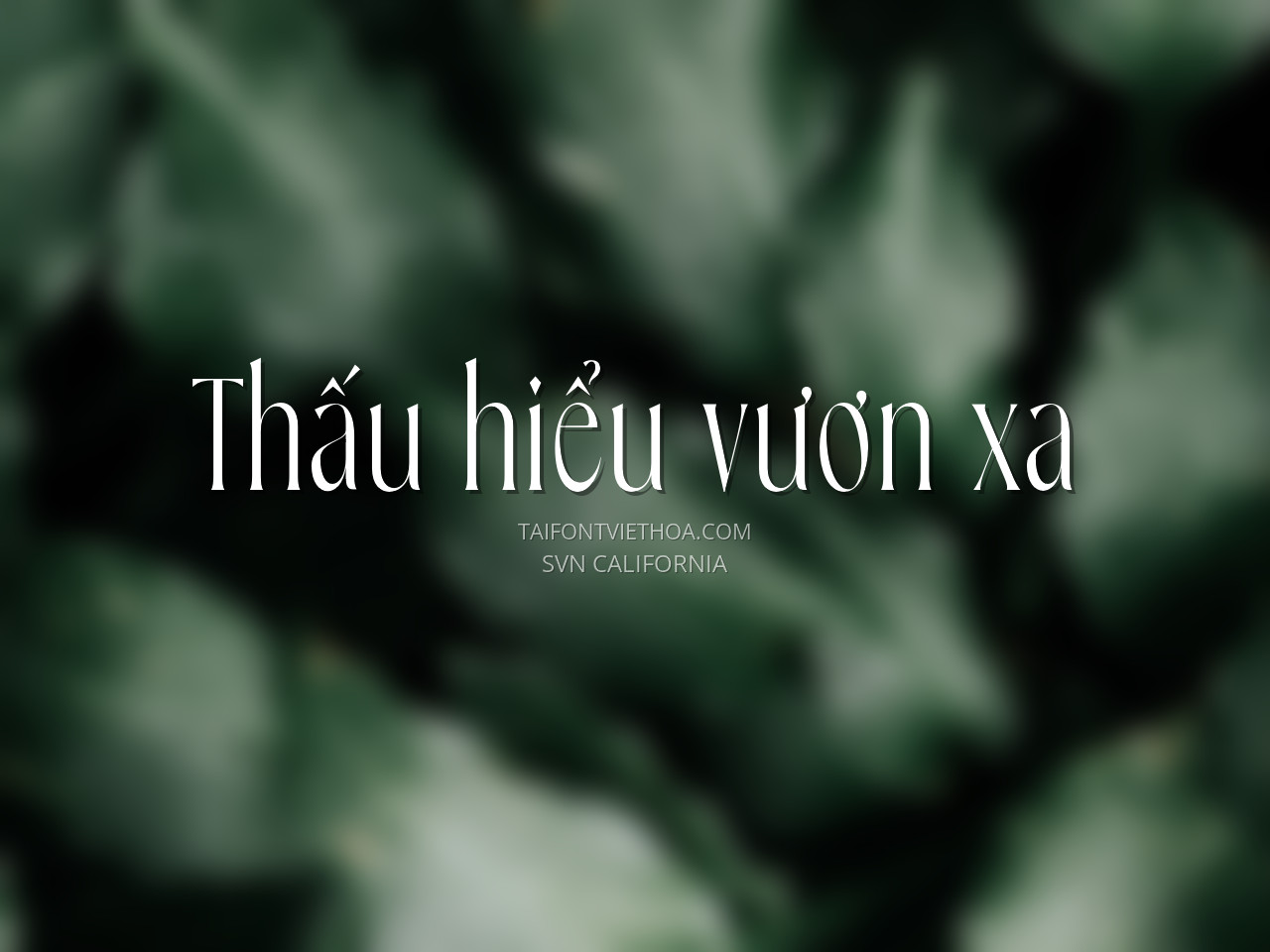
Font việt hóa SVN California
Giới thiệu về font SVN California – Kiểu chữ serif hiện đại, mềm mại và thanh lịch
SVN California là phiên bản Việt hóa của font California – một kiểu chữ serif mang phong cách hiện đại, mềm mại và rất thanh lịch. Font được thiết kế với các nét chữ cân đối, rõ ràng và có độ tương phản hài hòa, phù hợp cho các dự án thiết kế thương hiệu, in ấn và truyền thông cao cấp.
Phiên bản Việt hóa của SVN California đã được Taifontviethoa.comchăm sóc kỹ lưỡng, hỗ trợ đầy đủ dấu tiếng Việt cùng hơn 80 ngôn ngữ khác. Font giúp các nhà thiết kế dễ dàng áp dụng trong nhiều loại sản phẩm đa dạng mà vẫn giữ được vẻ đẹp trang nhã và chuyên nghiệp.
Thiết kế serif tinh tế – Ứng dụng đa dạng trong thương hiệu và xuất bản
SVN California sở hữu cấu trúc serif với các nét chữ mềm mại, uyển chuyển và đường cong tinh tế. Font phù hợp cho đoạn văn bản dài và tiêu đề, giúp tăng tính thẩm mỹ và sự chuyên nghiệp cho thiết kế. Phong cách của California mang đến sự hài hòa và sang trọng cho mọi sản phẩm thiết kế.
Ứng dụng lý tưởng: thiết kế nhận diện thương hiệu, bìa sách, tạp chí, brochure, thư mời, danh thiếp và các ấn phẩm quảng cáo cao cấp. Ngành nghề phù hợp: thời trang, mỹ phẩm, nội thất, giáo dục, xuất bản và các thương hiệu định vị theo phong cách hiện đại, thanh lịch.